Las 20 mejores Google Fonts para tu landing page
El uso de la tipografía web está experimentando un momento de gran creatividad. Y sin duda, las mejores Google Fonts han pasado a ser uno de los recursos más valiosos en este ámbito. Todo se debe a la naturaleza de código abierto de sus fuentes. De hecho, una de sus mejores características es que el gigante de Internet permite su uso tanto de manera personal como comercial.
Asimismo, la calidad de la selección es muy alta, ya que tiene en cuenta aspectos esenciales de la tipografía web y móvil. Como por ejemplo, la legibilidad y la accesibilidad.
La tipografía ha pasado a ser un elemento principal de diseño. Así lo apuntan las últimas tendencias. Y esto hace que las mejores Google Fonts se vuelvan más valiosas que nunca. Además, su interfaz y su sistema de descarga es tan intuitivo y cómodo que podrás comparar todas las fuentes y estilos disponibles hasta encontrar la tipografía ideal para tu landing page.
Las mejores Google Fonts fusionan tipografías en negrita, serifas y fuentes de pantalla, párrafos grandes, estilos decorativos y más. Tal y como apuntan las tendencias, Typography is the new black. ¿Cuántos estilos diferentes conoces?
Las mejores Google Fonts: 20 opciones para optimizar tus diseños
Con todo, si necesitas un pequeño empujón, aquí tienes una buena selección de las mejores Google Fonts del momento. Todas ellas destacan por su aspecto estético, ideales para crear landing pages atractivas. No obstante, lo que más destaca de todas ellas es su funcionalidad.
Las mejores Google Fonts son aquellas que están optimizadas para crear experiencias de usuario positivas, las más legibles y las más cómodas de leer en cualquier dispositivo.
1.- Lora
Lora es un serif contemporáneo bien equilibrado que tiene sus raíces en la caligrafía. Es un tipografía que crea un contraste moderado, lo que hace que se adapte bien a los textos.
Un párrafo redactado en Lora tendrá un aspecto memorable. Sobre todo debido a sus curvas creadas a partir del estilo serif. Además, la voz tipográfica general de Lora transmite perfectamente el estado de ánimo de una historia moderna, o un ensayo artístico. Lo que hace de esta opción una de las mejores Google Fonts para landings en las que se expongan historias, textos creados a partir del storytelling o testimonios.
2.- Karla
Karla es una tipografía de palo seco grotesco que incluye cierta modulación. Así como contraformas abiertas. Una de sus características principales es que el espaciado de sus caracteres es bastante abierto. No obstante, esto no tiene que ser una desventaja para los textos de tus landing pages. Al contrario.
Aunque el espaciado de sus caracteres puede resultar un tanto llamativo, se trata de una fuente con personalidad. Probablemente te mantengas en el top of mind de los usuarios gracias a esta peculiaridad.
3.- Frank Ruhl Libre
Frank Ruhl Libre es una versión de código abierto del tipo de letra hebreo clásico, el tipo de letra hebreo más popular en los medios impresos. Frank Rühl fue diseñado en 1908 por Rafael Frank en colaboración con Auto Rühl de la fundición C. F. Rühl de Leipzig. Aunque la versión final fue lanzada en 1910, muchos libros, periódicos y revistas israelíes utilizan a Frank Rühl como su fuente de texto principal.
Se trata de una de las mejores Google Fonts porque está diseñada para adaptarse a las demandas modernas, para ser legible en textos de formato largo, con y sin marcas vocales. Frank Rühl tiene proporciones de Sephardi (la altura del mem es aproximadamente 4½ anchos de carrera), y se basa aproximadamente en los tipos de letra venecianos utilizados por la impresora Daniel Bomberg.
4.- Archivo
Otra de las mejores Google Fonts es Archivo. Esta tipografía fue diseñada para ser utilizada simultáneamente en plataformas impresas y digitales. Las características técnicas y estéticas de la fuente están diseñadas para tipografías de alto rendimiento. De hecho, es compatible con más de 200 idiomas a nivel mundial.
Archivo viene de una familia grotesca de tipo de letra sans serif de Omnibus-Type. Fue diseñada, originalmente, para destacados y titulares.
5.- Fjalla One
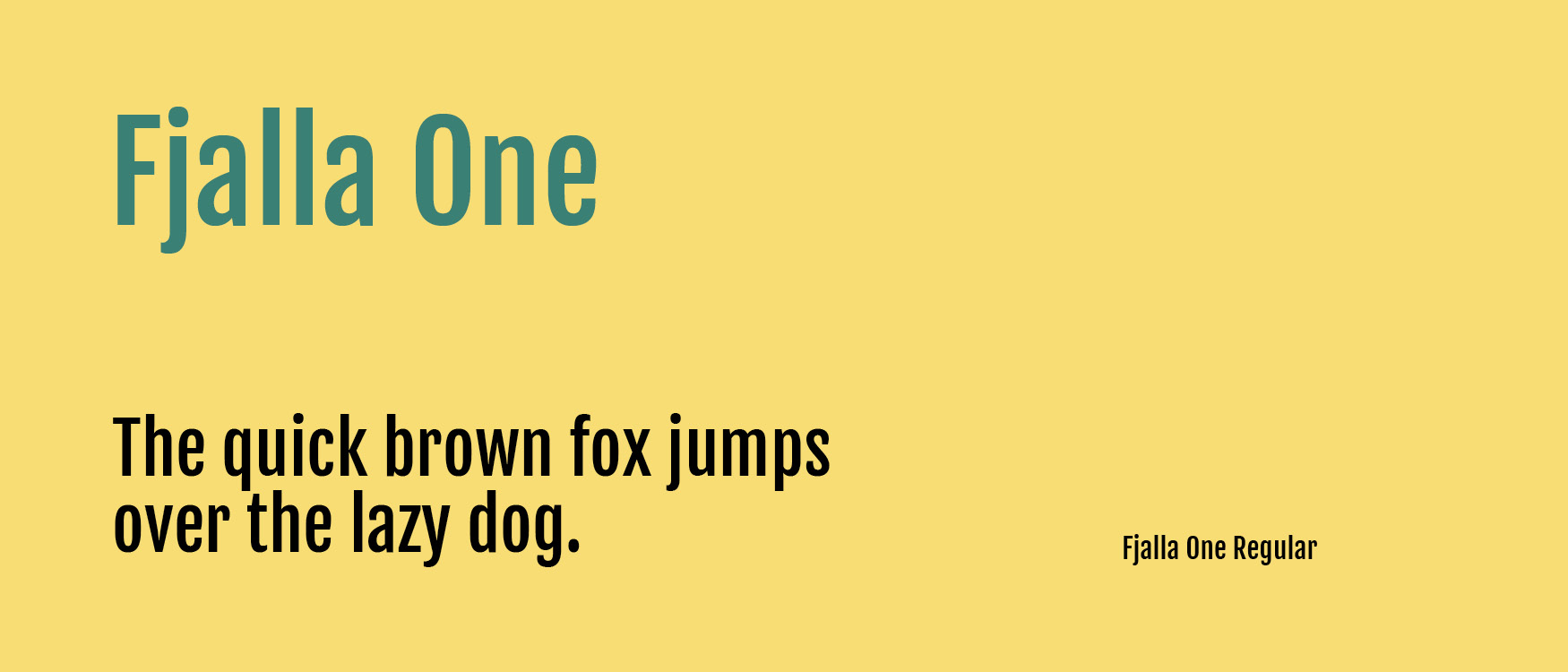
Otra de las mejores Google Fonts para destacar con los diseños de tus landings es Fjalla One. De hecho, esta tipografía destaca porque se ha ido ajustando cuidadosamente a las restricciones de la pantalla. Y gracias a ese trabajo, este tipo de tipografía puede utilizarse en una amplia gama de tamaños.
6.- Roboto
Roboto viene de familia de fuentes del tipo Sans-serif. Y Sans Serif es el tipo de fuentes tipográficas que destaca por evitar los adornos, las pequeñas terminaciones o remates. Lo que hace que sean las más recomendadas para utilizar en pantallas, de forma que eviten sobrecargar o cansar la vista y facilitar la lectura.
Fue creada por Google para su uso originalmente en el sistema operativo Android. Aunque posteriormente se extendió su uso al sistema operativo Chrome SO, y debido a sus características, es empleada actualmente en todos los productos, proyectos y servicios de Google. De ahí que sea una de las mejores Google Fonts del momento.
7.- Spectral
Spectral es la primera tipografía responsive de Google. La tipografía, diseñada por Production Type, es una serif que pretende romper con la idea de que las fuentes de palo seco son las únicas que se pueden adaptar a cualquier tipo de texto.
De hecho, los catorce pesos disponibles en Google Fonts convierten a Spectral en la tipografía perfecta para proyectos colaborativos o que han sido concebidos para ser visualizados en pantallas o dispositivos con diferentes tipos de resoluciones.
8.- Rubik
El estudio Hubert & Fischer firma el diseño de esta tipografía desarrollada para el proyecto de Google Chrome Cube Lab. La principal característica de esta familia de palo seco es que las todas las esquinas de sus caracteres están ligeramente redondeadas. Se trata de un pequeño detalle que aunque sea sutil, aporta un toque diferenciador. Es una de las mejores Google Fonts para aportar personalidad a los textos de tus landings.
9.- Source Sans
Source Sans Pro, es la primera familia tipografía de código abierto de Adobe. De hecho, fue diseñada por Paul D. Hunt. Es un tipo de letra sans serif destinado a funcionar bien en las interfaces creadas para proporcionar una buena experiencia de usuario.
10.- Cardo
Cardo es una gran fuente Unicode diseñada específicamente para las necesidades de los clásicos. Es decir, la utilizaban eruditos bíblicos, medievalistas y lingüistas. También funciona bien para situaciones en las que se necesita una fuente de estilo antiguo de alta calidad. De hecho, para campañas concretas o landings específicas, esta puede ser una de las mejores Google Fonts.
Cardo también contiene características que se requieren en tipografías de alta calidad. Como por ejemplo ligaduras, figuras de texto (también conocidas como números de estilo antiguo), mayúsculas pequeñas, y una gran variedad de caracteres de puntuación y espacio.
11.- Playfair Display
El fuerte contraste entre los finos y gruesos más su apariencia de romana moderna y sus pequeños detalles hacen de esta tipografía, una de las mejores Google Fonts para crear titulares o textos destacados.
12.- Montserrat
La diseñadora Julieta Ulanovsky consiguió inspirarse con los rótulos del histórico barrio de Montserrat, en Buenos Aires, para diseñar una de las tipografía de palo seco que, actualmente, forma parte de las mejores Google Fonts.
El boom de este diseño ha dado lugar a diferentes variaciones estilísticas. Así, Montserrat ha ido creciendo y ahora acoge 16 fuentes con las variantes Alternates y Subrayada.
13.- Work Sans
Work Sans es una familia que fue desarrollada por el diseñador australiano Wei Huang. De hecho, una de sus principales características es que está inspirada en las primeras tipografías de palo seco del siglo XIX. Y esto hace que incorpore atributos formales como la neutralidad, la simplicidad y una geometría muy peculiar.
Su escaso contraste y la apertura de sus contraformas le proporcionan un aspecto amigable. Sus 9 variantes (desde thin hasta black) convierten a una de las mejores Google Fonts en versátil y útil para el trabajo con diferentes jerarquías de texto.
14.- Cormorant
Sin duda, una de las mejores Google Fonts que probablemente, ya conocerás. Está inspirada en el legado de Claude Garamond y está diseñada por Christian Thalmann.
Cormorant lo tiene todo. Sobre todo, destaca porque contiene la esencia de la tipografía romana clásica por excelencia. Se trata de un familia display, lo que significa que está diseñada para titulares y textos destacados. La fuerte influencia histórica de sus formas hace que el lector se transporte al mundo de la literatura. Principalmente porque esas características le dotan de un tono sobrio y solemne.
15.- Concert One
Concert One se posiciona como otra de las mejores Google Fonts por ser una tipografía redondeada y grotesca. Está inspirada en las letras 3D del siglo XIX de un folleto que anuncia un concierto de cámara. Por lo que puede aportar mucha personalidad en landings específicas.
16.- Yatra One
Yatra One es una fuente devanagari y latina inspirada en la señalización pintada a mano del ferrocarril local de Mumbai. Esta tipografía conserva el carácter especial de la señalización pintada con pincel al presentar cortes angulares y nudos abiertos.
17.- Rakkas
Rakkas es un tipo de letra de visualización de un solo peso que admite los scripts árabes y latinos. Los dos guiones comparten un estilo unido, sin pretender ser el otro, y cada uno destaca por sí mismo.
El diseño árabe está inspirado en las letras de Ruq’ah, en carteles de películas egipcias de los años 50 y 60, y hace uso de alternativas contextuales para emular la caligrafía. Ofrece diferentes formas para muchas posiciones de letras y se coloca en cascada verticalmente, dando al usuario la oportunidad de jugar.
18.- Lato
Lato es una familia tipográfica sans serif desarrollada en el verano de 2010 por el diseñador Warsawukasz Dziedzic. Al trabajar en Lato, se intentó equilibrar cuidadosamente alguna de las prioridades que podían resultar conflictivas.
Para ello, se pensó en crear un tipo de letra que pareciera bastante «transparente» cuando se usara en el texto del cuerpo, pero que mostrara algunos rasgos originales cuando se usara en tamaños más grandes.
19.- Abril FatFace
Abril Fatface es parte de una familia más grande que incluye 18 estilos para todos los usos de Pantalla y Texto. Los pesos de titulación son una renovación contemporánea de los estilos clásicos de Didone.
Muestran neutralidad y tienen una fuerte presencia en la página para atraer la atención del lector con la tensión medida por sus curvas, buen color y alto contraste. Precisamente, esas son las características que convierten a esta tipografía en una de las mejores Google Fonts para utilizar en tus landing pages.
20.- Open Sans
Open Sans es un tipo de letra humanista sans serif diseñada por Steve Matteson, Director Tipo de Ascender Corp. Esta versión contiene el conjunto completo de caracteres, un total de 897.
Open Sans fue diseñado con una tensión vertical, formas abiertas y una apariencia neutral pero amigable. Fue optimizada para las interfaces de impresión, web y móvil, y tiene excelentes características de legibilidad en sus formas de letras.